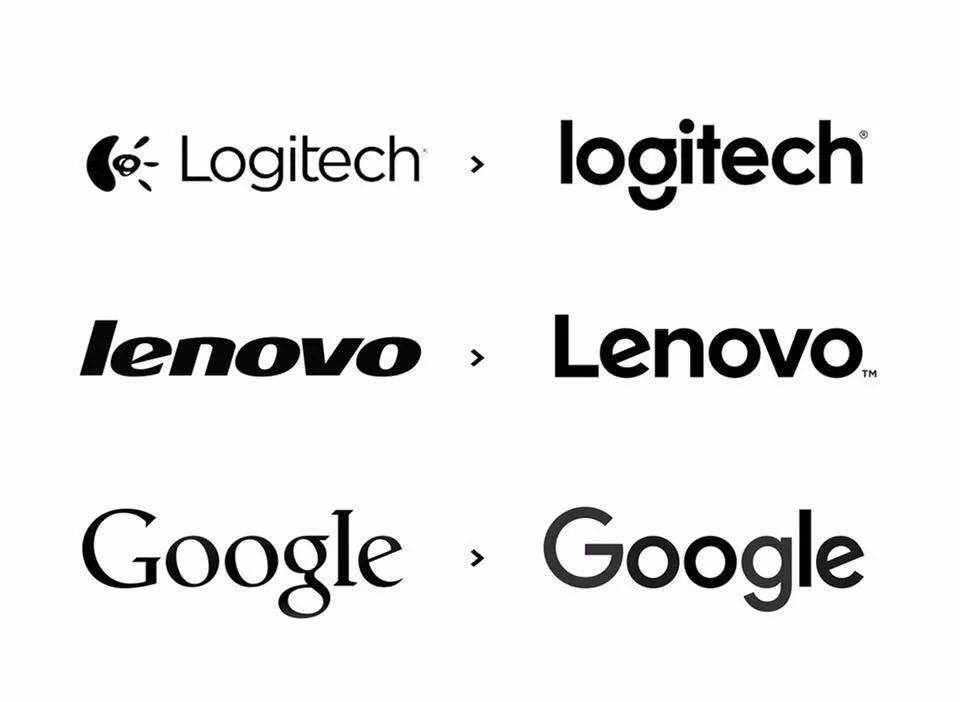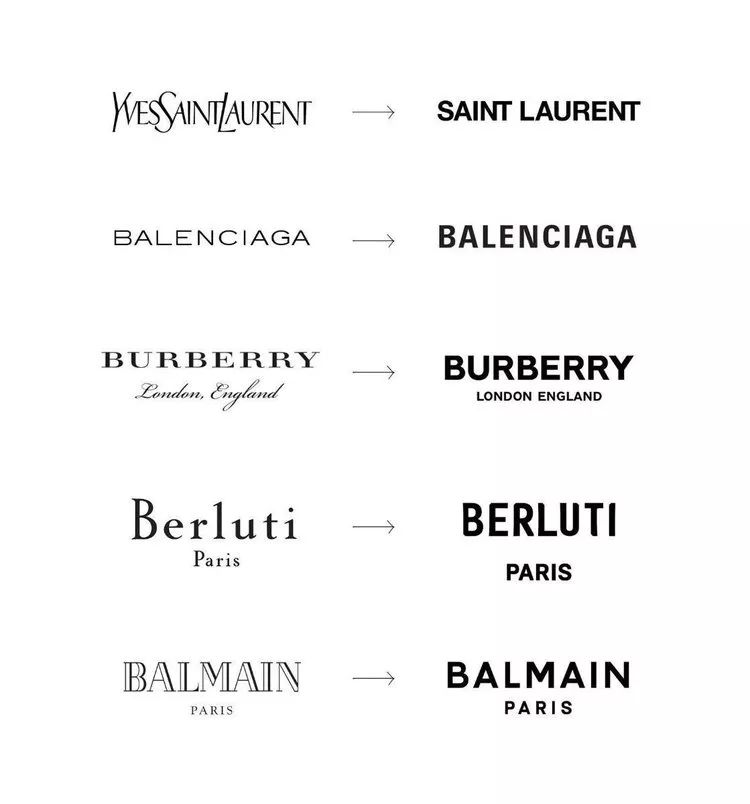
极简化正在杀死设计行业?设计师是怎么看待LOGO同质化的
阿信说:今天我们来和外国设计师一起来看看大家都是怎么看待LOGO同质化的!
各大服装品牌的标志更新基本上落下来帷幕,更新之后的风格真的让人难以一眼区分到底它们谁是谁失散多年的兄弟姐妹父母亲。。。让我们伴随着国外同行们的一些观点来观望一下这些品牌各自摒弃原本各有特色的品牌LOGO元素之后还剩下了什么?
🤔为什么奢侈品大牌们都换了一样风格的LOGO?
🤔为什么这些大牌有如此迥异的初衷,但却做着一样的行为?
🤔那穿戴Balmain的消费者是不是和穿戴Saint-Laurent的一样了?
🤔最本质的东西不应该是产品本身而不是把精力主要放在修改logo吗?
🤔对于我们生活环境而言,品牌变得更谨慎不是一件好事吗?
作为一个大家可能感兴趣的开放性话题,我把它们放到了社交媒体上并筛选出了一些具体不同代表性观点的回复:
比较宽容的设计师们:
设计师L:“一个品牌的表达不再受限于神圣的标志。人们都开始用一个不加装饰的字体来代替了其他的模式。。。我也很喜欢不同风格的充满表现力的logo,它完成了人们的需要重新认知的工作,但是我也承认一个用字体表现为主的logo品牌不应该长时间成为一个视觉识别的关键。”
设计师N:“从品牌形象全球化那一刻浮现起我就没有感到太震惊,毕竟这也减缓了一个形象识别老化的速度。”
稍微激进的设计师们:
设计师M:“在我们那个年代的形象。。。传播与品牌都尤为谨慎,看起来平淡无奇,在缺少被取悦的情况下宁愿避免对大众做不讨喜的事情。”
设计师Q:“我觉得新的标志们变得如此同质化是一件很可惜的事。在成百上千万的众多品牌当中若你没有明显的差异性如何与他人区别开来?若这些logo都这么相似,他们的品牌在商业的道路上该如何定位并确立自己的旗帜?要是在大商场的卖场里岂不是显得更糟糕?不管怎样,当下的这样视觉呈现的选择是在让人惊讶甚至失望,就好像我们开始在抑制创意力一样。。。我想知道这是不是我们职业贬值的第一步?”
设计师C:“这个形象识别的工序走向了让每一个品牌独特性灭亡的道路。我觉得这让人感到悲伤而且对于这些有权利的品牌来说这样很危险。就好比如何让一个没有个性的东西来体现它的性格?我看待一个品牌的logo好比一个个体的性格,每个人都可以通过他不同的文笔来展现自己的个性(尽管有些部分很相似)。”
设计师G:“就我而言,就好像我们跑着步去见客户?(意为没时间做设计)我们在说marketing的时候好像会提到差异性。。。尤其是品牌!但现在这样的新趋势好像我还没太搞懂。”
持有怀疑态度的一些客户:
Nicolas(法国百年卖酒连锁品牌):
我们还以为自己是在测视力。这很简洁但并没有很明显的区别,还需进一步确认看看每个logo都是如何展延开来的(原意为每个logo都是一个地方延展出来的)。
Antoine:
他们都是找一家品牌公司做的吧。。。国际性的合作,全球化的视野。。。产品的绝对产业化以实现最大利润化。
Jean-Jacques(法国服装品牌):
我觉得有的牌子就是在玩“anti-logo”,只有他们的品牌的名字,充满魔力的,足以。。。
Stéphane:
我准备步“同质化”的后尘来做logo了。。。
一方面设计师对这种极简化自愿地站在了愤怒的广大群众这边。但另一方面,他们又不能阻止对这种极简化抱怨着迷或是漠不关心。这些网上的对话完美地反应了他们的处境。 不要同时行走在四个道路上(意为直奔主题)。那些让设计师们抓狂的,是极简化在慢性杀死这个行业!
所以我们不断产生一个想法,要在所有场合跳出来抗议这个飞速发展的同质化,必须让人们明白视觉识别的核心利弊是让一个品牌让人看到并认可。毫无疑问,从竞争中脱颖而出成为一个不可避免的角色,原创性与独特性都是作为设计师一个重要的利弊。就好比我们经常评论一个艺术家的造诣或一个演员的独创性,他的风格。
让设计师感到害怕的同质化!
同质化=削弱附加价值=设计师专业化的贫乏
所有我们思考的这些双重矛盾性也正是由于这个极简化对于设计师而言同时也是个极高的难度。包豪斯学院与及勤奋的学生们好几代人一直在探索简约风格。
Wim Crouwel,Bruno Monguzzi(巴黎奥赛博物馆logo设计者),Ruedi Baur(巴黎蓬皮杜博物馆logo设计者)亦或Philipp Apeloig,还有许多不同时期的创造者们都痴迷于这种风格上。
如果我们把它与建筑设计中的风格做个对比,我们可以做个简单的对比并看到相比造一个房子而言,若我们不想让它在第一次台风中就倒塌的话当然是越精确,越简单和越严密越好。对于logo而言也是一样的!
在绘制一个logo的时候最好是绘制一个几乎建筑设计式的结构系统来确保它的阅读的平衡性以及不同类型下使用的适用性。但谁又会想要将工地临时搭的棚作为住宅?那么使用简单易用的人体工程学是否又说明了缺乏情感与风格呢?
“形态,就是浮上表面的本质。”
– Victor Hugo
文章开头图片中的品牌字标并不能很好的体现它完整的视觉风格。其实它还缺少了一个重要的元素,一个符号(我们常说的视觉锤)!
当我们要开创一个公司的时候,我们会先选择一个名称,然后设计logo并把它拿去相关部门注册保护起来防止抄袭。这些步骤我们可以独立去完成或者是在设计师的陪伴下完成,也可以找个专业的律师。但是我强烈建议在这种情况下既需要设计师也需要律师的同时陪同。
然而一个律师并不会对你的字体感兴趣,他只对你公司的价值感兴趣。一个好的律师不会建议你用一个普通的名子或是描述您的活动的名字。若给一个餐厅命名“Table(桌子)”或“Manger(吃)”亦或商业街道的门牌号,这些都不会起到独特性的作用。若在争议和潜在诉讼的情况下,很难去捍卫一个名为“Le Restaurant(饭店)”的饭店的独特性。
一个品牌在什么情况下
才会变得独一无二?
就是在这一个符号开始浮现出表面。一些品牌就很善于运用他们的符号(视觉锤),以至于人们都忘却他们品牌名称的样子(指字标)!你们谁还记得Apple或者WWF的字体长什么样吗?
在有的工业领域里面符号的存在
是不可避免的:
汽车与科技行业就是个很好的例子。在汽车上没有品牌标志的符号是不可能的!同样的在软件的app上也不可能没有icon!我们有许多的理由去使用这些符号但是只有一个理由至关重要并且对这些极度相似的logo会产生直接的愤怒:
情感关系!
客户们和这些品牌维持着一种双向的情感关系。一方面品牌在寻求以多种不同的精力去照料着他们的用户(通过质量,体验,包装,语气,惊喜)从而形成一个凝聚力。另一方面,客户们(有时不知不觉)不断增加他们对这个品牌的热情。
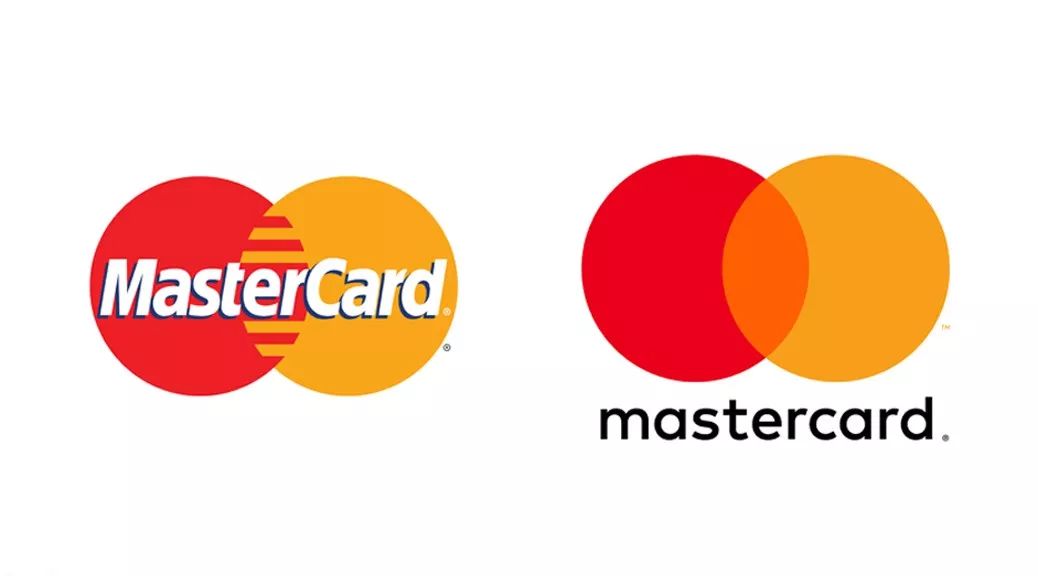
(万事达新LOGO最后只剩下一个图标)
与其他的热情一样,Gap这个新标会产生很多例如新产品发布之后伴随而来的议论纷纷的事情。但这个诞生可能会使之陷入巨大的不解与愤怒当中,就好比要撤销掉一个产品或者删除其中一个功能一般。
我还记得当时Gap要更改logo时客户们的不满的情形。新logo在大众狠狠的意见对抗之下Gap最终还是选择了让步。在7天时间里,还有75万的粉丝在Facebook的页面上的抗议,该公司选择了退缩。这又是一个把logo扔进logo滚筒洗衣机里并以Lineal字体为主要形式的故事。
(悲剧之前/悲剧中/悲剧之后,2010年)
从Gap的案例来看,它的新logo看起来像那么回事但又什么也不是。它看起相当冰冷而且让人很难适应!很难理解这个品牌想要通过这样的改变来得到什么?作为一个设计师,我的首要工作就是去理解它的背景,将自己沉浸在着手进行的品牌历史环境中。在深入研究学习的过程中慢慢的就会得到一些拼凑成形的符号。这便是我们在艺术或者设计学院所接受的“bien faire notre travail(做好我们的工作)”的教育。
“设计是你的品牌无声的大使。”
– Paul Rand,IBM logo设计者
对我而言当这个品牌符号(视觉锤)很谨慎地渗透在品牌的方方面面的时候设计任务才是成功的。Logo,字体,传达的调性,包装,还有其它种种我们当今称之为用户体验的东西很大程度上都是由设计所驱动的。 我们所称之为“Branding”的这个方法的第一步是围绕着logo的创意策略展开的。
对我个人而言这是我整个职业中最喜欢的部分。只有这个部分是我们可以向企业的领导提出所有实实在在策略性的问题。当这项工作由管理/用户/设计师之间很好的完成后便会浮现出一些很接近利弊的3个部分:
赢利与领导(Direction)
愉快与使用(User)
独特性与掌控(Designer)
大众的眼睛是雪亮的!那些太简单的logo通常会急速地狠狠被批判是因为它们让客户还在发现探索品牌阶段时就让人失望了。他们剥夺了用户们一部分感官的同时还想让品牌变得平易近人。
归根到底奢侈品牌们越来越多地将自己定位成了寻求方便的地方。 当人们把BALMAIN写成BERLUTTI时,就像写EAU(水)或GAZ(气)。 要成为简单的且变得平易近人是高级商学院的重要的科目之一。 当您的品牌变得简单并平易近人时,那就是胜利! 这时候您就能聚集一个庞大的用户社区群体,并变得至关重要。 这个策略性的诀窍可以避免从正面将客户当成傻子的冒险。
©Apple Inc.
Apple在超过20年的时间里都在通过它大胆的设计来强调“Think Different”,从第一代iMac和iBook五彩的苹果形状还有能让人发现机子内部的半透明材质。这些机器们确实是从里到外一样的美丽,但主要还是它跟别的电脑巨大的区别!(那个年代谁会大胆到去买一个苹果形状的电脑?)如果他们的成功与创新产品和设计有关,一些观察人士则认为在他们的marketing里不存在设计:黑色简洁的字体,白底,轮廓化的图像。即使在复制这些用户界面(MacOS或iOS)之前,有一个更简单复制这个方式的方法适用于市场。在2000前后的时期所有的公司都希望在Apple拥有一个网站。
同质化的优点无疑是使用人体工程学的最佳使用民主化从而让一个点击就能实现简单购买。
那风险是什么?这种快速的同质化可以追溯到企业的logo甚至于企业品牌的DNA。这个推论其实很简单:
通过模仿先行者,我的品牌变得有保障并且易识别,
而且我还能确信我不会错。
由此就会引申出几个问题:
1.复制前人的做法能否做到像它一样成功?
2.若所有人都这么做之后,那就再也不存在什么可视性/易读性了?
假设你来自另一个星系,你对我们周围的品牌历史一无所知,你很难知道Céline在做什么吗? 又或是Krups卖的是和Lancel一样的产品吗?。
在时尚和其他地方一样,有一些经典的logo到现在还没变(就目前而言!)。设计师Etienne Mineur在这个主题上与我分享了他的一篇非常好的文章“Un safari typographique dans ma penderie(在我衣柜里的字体旅行)”。 这篇文章试图去剖析2006年时尚圈里的标志风格的不同流派。 我真诚地建议你们浏览看看。 更有趣的事,谁能屈服于一种共识的重新审视的诱惑并坚持下去!
然而在除了时尚界之外的其他领域,有些公司还是成功的在没有主视觉符号的情况下表现出其独特性!
这些像迪士尼这样的大企业在他们所有设计都融入了品牌自身的DNA。当我们看到Walt Disney如签名般的logo,就好像看到所有的动画都获得了生命力一般!当我们看到Harley-Davidson的纹章我们看到皮质感还有到处纹了身的大胡子!那Virgin呢?好比Mike Jaegger在我CD上的题词?(请阅读Richard Branson在写了Sex Pistols之后对这个独特logo的解释。) 而Paul Rand的IBM logo的成功之处在于它就是一个icon!虽然它能够在那个年代将电脑表现出是一种史前科技,它已成为一个绝对地位的icon。无论趋势如何,领导者始终是在前面。不得不说这个logo它确是一种独一无二的风格!
“这个视觉元素是如此的强烈,即便我用这八个线条去拼写Apple,
人们首先想到的还是IBM。”
– Michel Chanaud,《étapes》杂志总编
谁又会是下一个迈入同质化的品牌呢?让我们拭目以待。。。